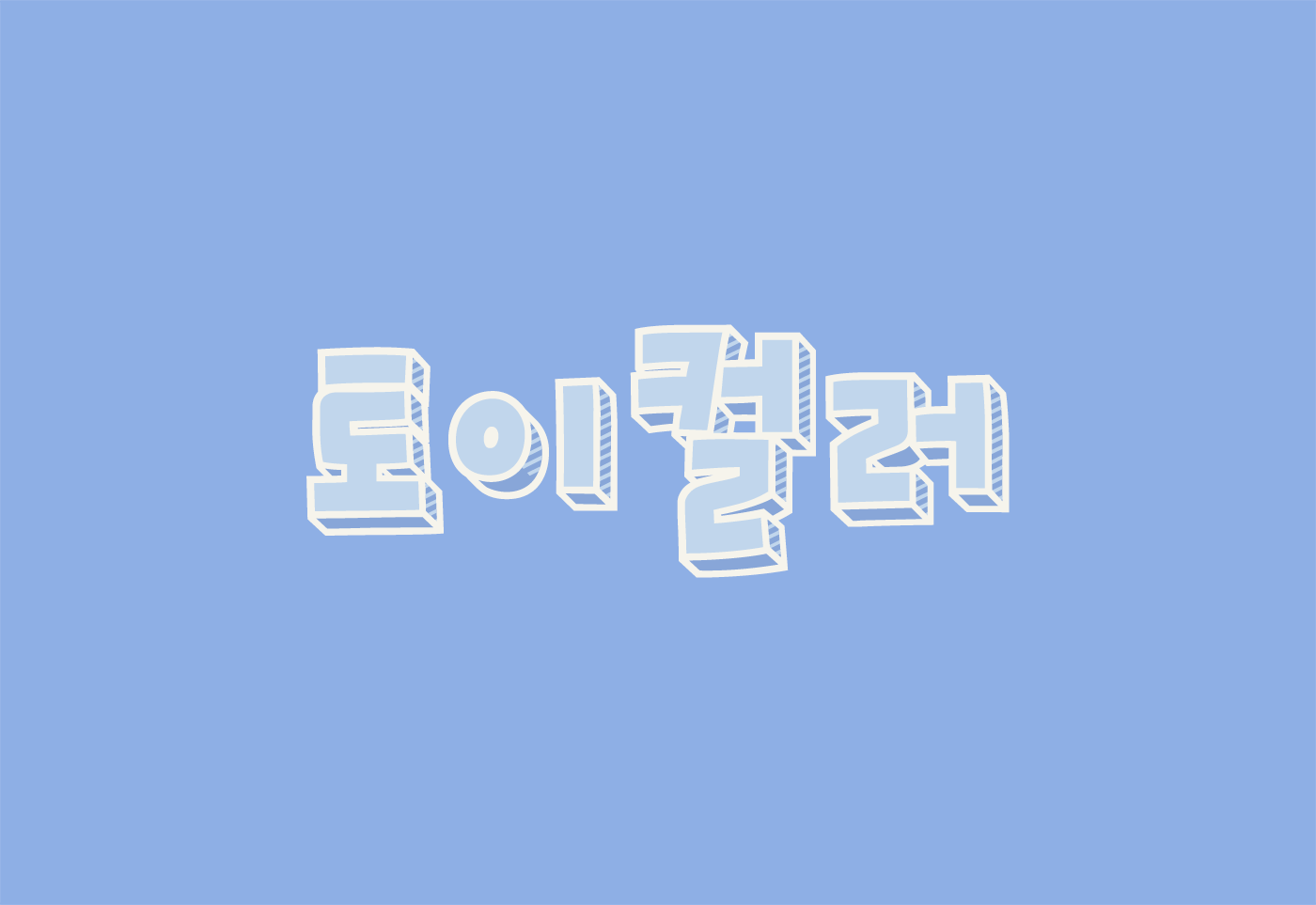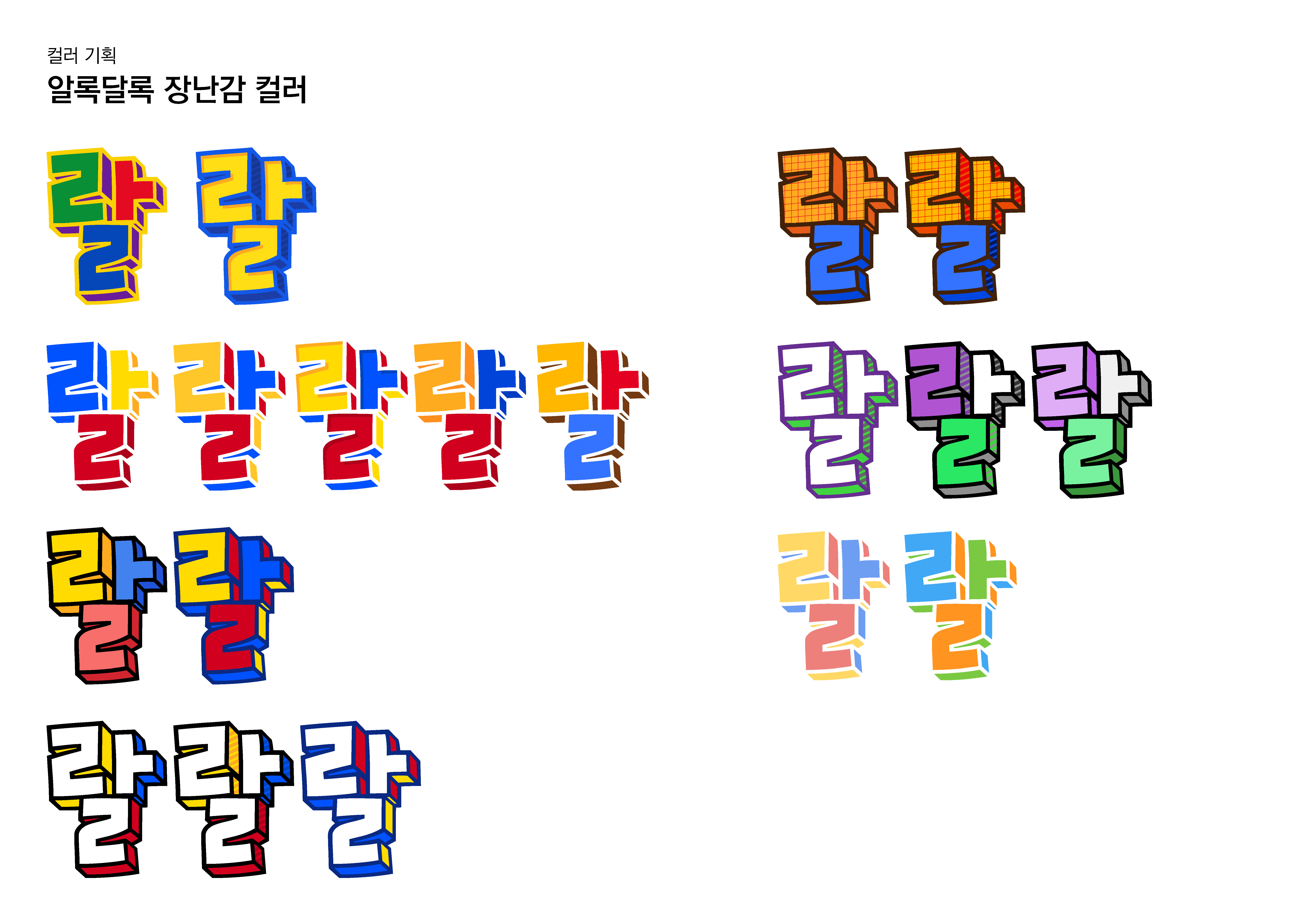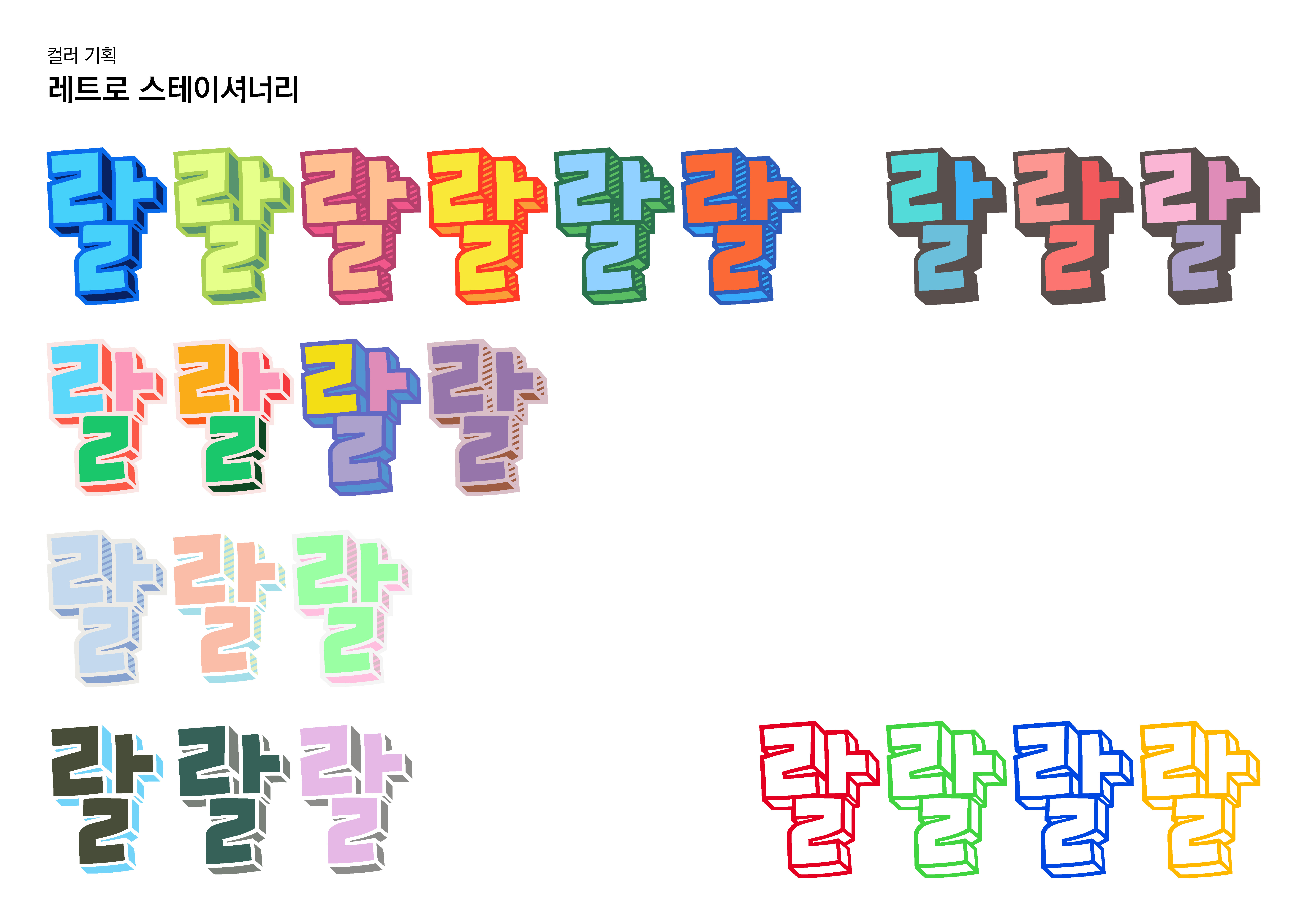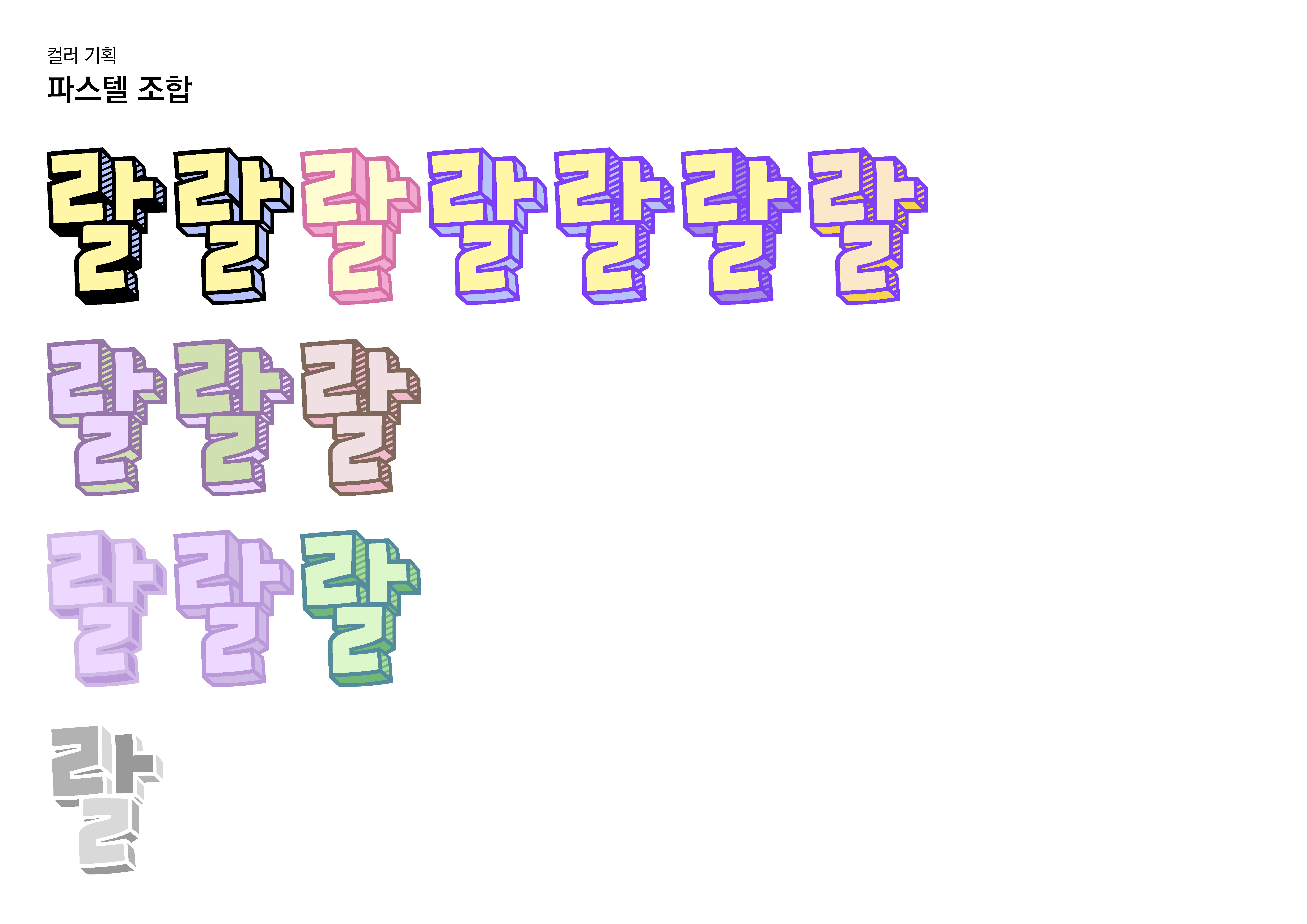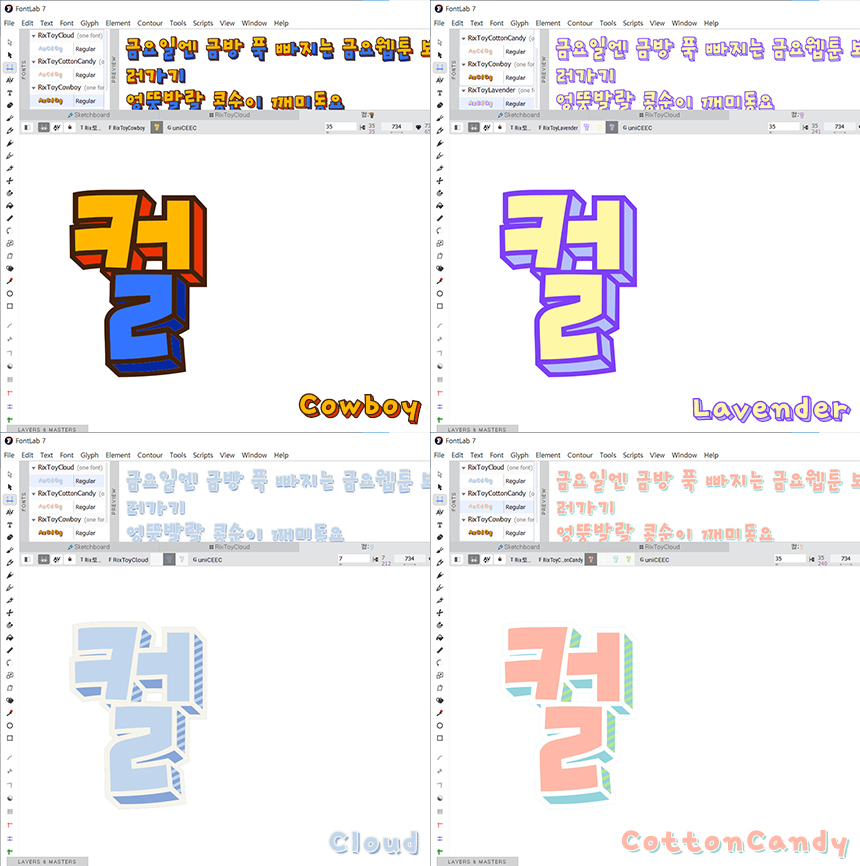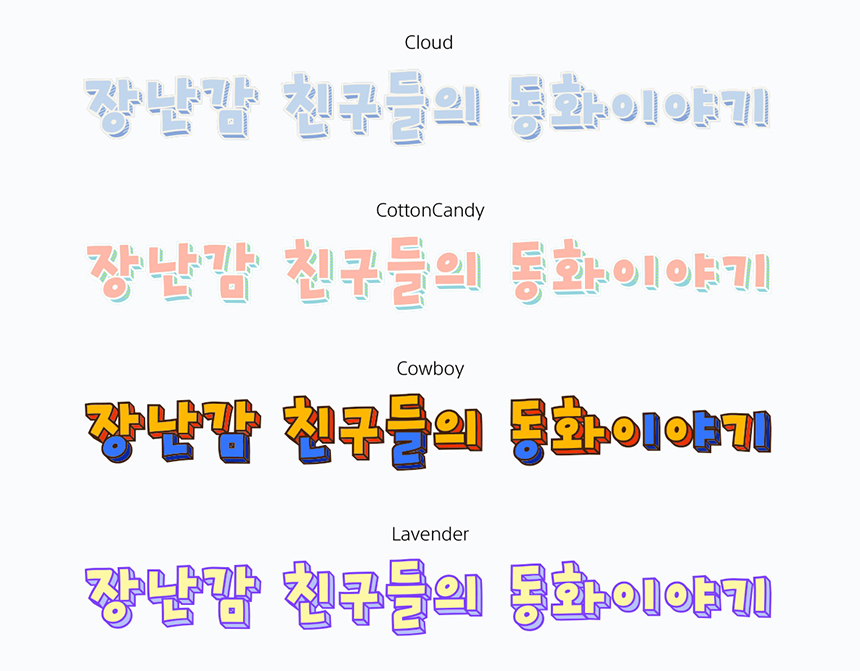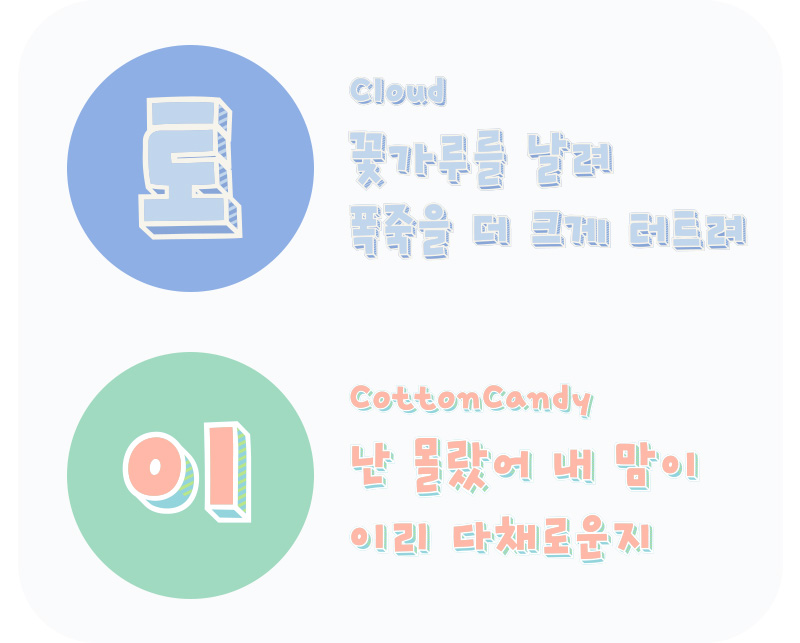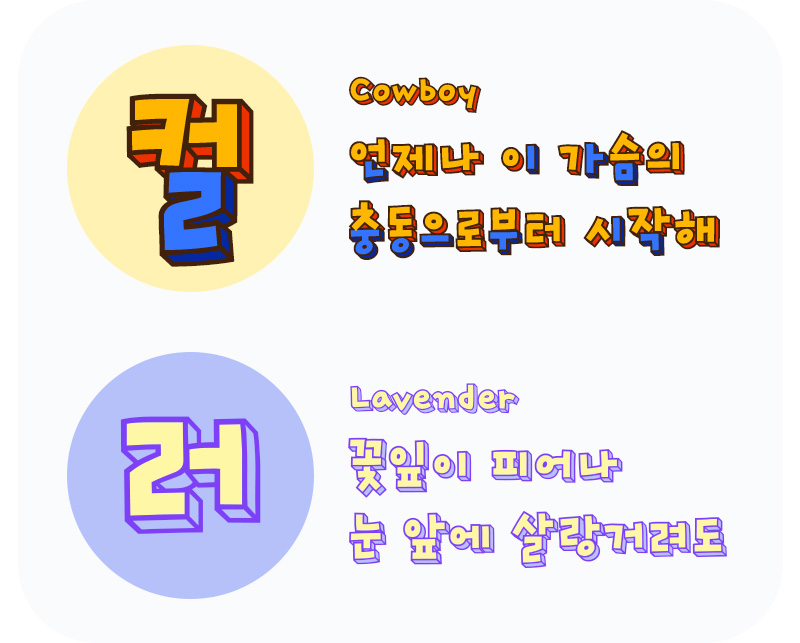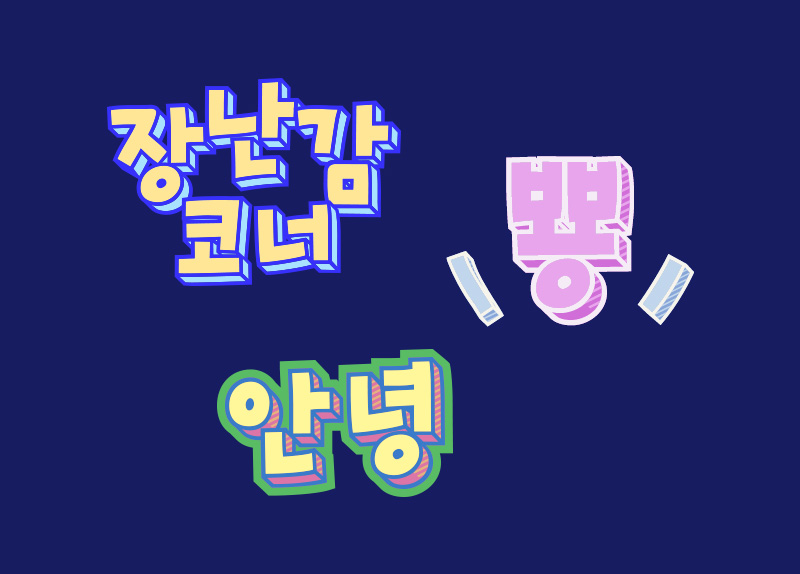
안녕하세요. 오늘은 신나고 즐거운 달 5월과 잘 어울리는 신규 폰트, 「Rix토이컬러」을 소개합니다! Rix토이스토리 시리즈의 글꼴로 이번에 4가지 새로운 컬러와 입체 효과를 조합해 새롭게 출시된 서체입니다. 보기만 해도 즐거움이 느껴지는 Rix토이컬러, 릭스폰트에서 최초로 제작한 컬러폰트라 더 특별하게 느껴지는데요. 제작을 맡아주신 윤유민 디자이너와의 인터뷰를 통해 폰트가 어떻게 제작되었는지, 어떤 과정이 있었는지 함께 알아볼게요 :)
Rix토이컬러 폰트 제작을 어떻게 맡게 되셨는지, 또 컬러폰트로 기획하시게 된 배경이 궁금합니다.
다양하게 조합하여 사용할 수 있는 ‘Rix토이스토리 시리즈’를 컬러폰트로 제작해보면 좋을 것 같다는 내부 의견이 있었어요. 저는 폰트릭스 입사 전까지 그래픽 디자이너로 일했기 때문에 컬러를 활용하는 감이 제일 트렌디할 것이라는 팀원들의 추천으로 제작을 담당하게 되었습니다. 매체에서 많이 쓰였던 친숙한 폰트였기 때문에 기쁜 마음으로 즐겁게 작업했습니다.
컬러를 기획할 때 토이스토리 폰트의 특성인 레이어를 3중~4중 결합하여 보다 적극적인 그래픽 조합을 시도했고, 여러 컬러 폰트들의 사례를 찾아보며 여태 없던 방식의 조합을 구상하게 되었습니다. 색감의 조합에 따라서 사용성 또한 다양해지는 효과를 기대하며 제작했습니다.
5월에 출시되는 폰트답게 톡톡 튀는 컬러감과 플레이풀한 분위기가 눈에 띕니다. 폰트의 매력 포인트들을 마음껏 자랑해 주세요!
Rix토이스토리의 가장 큰 매력은 컬러폰트답게 역시 색감이라고 생각합니다! 컬러를 정할 때 많이 고민했는데요. 토이스토리의 주제에서 파생한 알록달록한 장난감 색채, 그 장난감들이 시간이 지나 빛이 바랜 듯한 빈티지한 색감, 활용성이 좋은 파스텔 색감 이렇게 크게 3가지로 패밀리를 꾸려보았습니다.
상세한 구성으로는 만화 주인공의 명랑함이 떠오르는 조합의 카우보이, 늦봄의 꽃 축제 같은 싱그러운 색감의 라벤더, 낮은 채도로 빈티지하면서도 맑은 하늘을 연상하게 하는 구름, 어릴 때 즐겨 먹던 솜사탕 같은 알록달록한 색감의 솜사탕이 있습니다. 5월에 출시되지만, 네 가지 스타일 모두 포근함과 아기자기한 느낌이 들어있어 계절과 상관없이 사용해 주시면 좋겠습니다.
폰트와 찰떡궁합을 이룰 콘텐츠나 디자인을 추천해 주신다면?
아기자기하거나 귀여운, 또는 포근함과 따듯함을 강조하는 콘텐츠나, 추억/동심에 관련된 콘텐츠에 사용하면 좋을 것 같습니다! 방송/영상 자막, 장난감 관련 코너나 콘셉트가 있는 카페의 간판이나 메뉴 디자인에도 잘 어울릴 것 같습니다. 개인적으로 요즘 오은영 박사님이 출연하는 ‘요즘 육아 금쪽같은 내 새끼’를 애청하고 있는데요, 그런 프로그램에서 본다면 정말 반가울 것 같습니다 ㅎㅎ.
● 색깔 있는 즐거운 폰트
4가지 스타일을 가진 컬러폰트로 재탄생한 Rix토이컬러! '컬러폰트'는 글자의 모양뿐 아니라 색상 데이터가 글꼴에 포함되어 있어 별도의 수정 없이도 컬러나 질감을 그대로 사용할 수 있다는 장점이 있어요. 보는 것만으로도 즐거움이 넘치는, 다채로운 매력의 글꼴들을 하나씩 만나볼게요😉
먼저 빈티지한 장난감을 모티브로 한 토이컬러Cloud 와 토이컬러CottonCandy 입니다. 차분한 하늘과 구름, 그리고 달달한 솜사탕이 떠오르는 컬러죠? 같은 디자인이라도 이렇게 색상과 패턴으로 다른 느낌을 낼 수 있다는 게 컬러 폰트의 매력인 것 같아요!
만화 주인공이 떠오르는 명랑한 색채의 토이컬러Cowboy는 쨍한 컬러감과 자소에 다른 색을 넣은 것이 포인트입니다. 써보면서 어떤 자소에 컬러가 달라지고 어떻게 표현되는지 보는 것도 재미 요소랍니다. 그리고 봄과 라벤더 꽃 색감을 담은 토이컬러Lavender는 아웃라인 컬러를 진하게 표현해 부드러우면서도 깔끔한 디자인이 예쁜 폰트입니다.
기존 토이스토리 시리즈의 글꼴에는 Rix토이스토리를 베이스로 다양한 입체 효과를 조합한 토이쉐도우, 토이화이트, 토이그레이, 토이블랙 이렇게 5가지 폰트가 있는데요~ 이번에 새롭게 출시된 Rix토이컬러와 이전에 제작된 토이스토리 시리즈 서체들과의 조합도 기대가 됩니다✨
● 재미를 주는 입체 효과
더 다채로운 스타일과 색을 입히고 싶다면? Adobe Illustrator에서 폰트의 윤곽선(Create Outlines)을 만들어 다양한 컬러로 바꿀 수 있습니다. 새롭고 다양한 조합을 통해 나만의 폰트를 완성해 보세요!
영문, 숫자, 기호, 특수문자 등에도 각각의 스타일이 적용되어 있어 용도에 따라 재미있게 활용할 수 있습니다. 그래픽적인 특징과 입체 효과가 눈을 사로잡기 때문에 아무래도 주목성이 필요한 영상 타이틀이나 자막에 요긴하게 쓰일 것 같아요.
● 이렇게 활용해 보세요
색다르고 신선한 컬러 조합과 입체 효과로 영상의 타이틀, 자막에 활용하기 좋습니다. 재기 발랄한 폰트의 형태가 아무래도 아이들 관련 콘텐츠나 즐거운 예능, 애니메이션 등에 잘 어울릴 것 같아요.
쉽게 읽히고 컬러풀한 재미있는 서체와 직관적이고 심플한 일러스트를 활용한 북커버 타이틀은 책의 내용을 궁금하게 하고 아이들의 이목을 끌 수 있습니다.
이미 Rix토이컬러의 바탕 디자인이 되는 Rix토이스토리 시리즈 서체들은 위와 같이 영상 자막이나 책 표지에 다양하게 활용된 바 있습니다. 이번에 출시된 토이컬러 폰트와 함께 앞으로 더 다채로운 활용이 가능할 것 같아요!